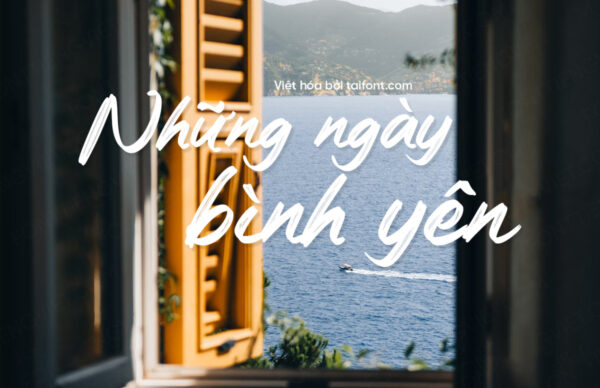
Giới thiệu về Font TF Realistic Theory Việt hóa
TF Realistic Theory Việt hóa là một font chữ Brush độc đáo, nổi bật với thiết kế tự do, phóng khoáng và đầy cá tính. Font này mang đến vẻ ngoài ngẫu hứng, năng động và rất riêng, gợi cảm giác về những nét cọ được phẩy một cách tự do, đầy năng lượng. Đây là lựa chọn lý tưởng để tạo điểm nhấn thị giác mạnh mẽ và gây chú ý ngay lập tức, đặc biệt trong các thiết kế liên quan đến du lịch, mỹ phẩm và các lĩnh vực đòi hỏi sự sáng tạo.
Với đặc điểm là nét brush to, đậm, dứt khoát và tính thẩm mỹ cao, Realistic Theory là lựa chọn hoàn hảo cho các thiết kế muốn truyền tải sự mạnh mẽ, hoài niệm và sự độc đáo, đặc biệt là trong các lĩnh vực:
- Thiết kế du lịch: Hoàn hảo để sử dụng cho logo các công ty du lịch, tiêu đề tạp chí du lịch, hoặc các ấn phẩm quảng bá tour. Nét chữ mạnh mẽ của font giúp truyền tải cảm giác phiêu lưu, khám phá và đầy năng lượng, thu hút những người yêu xê dịch.
- Thiết kế mỹ phẩm: Lý tưởng cho bao bì, nhãn mác, hoặc các ấn phẩm quảng cáo của các sản phẩm làm đẹp, mỹ phẩm. Font này giúp truyền tải vẻ đẹp tinh tế, sang trọng và độc quyền của sản phẩm, nâng tầm giá trị thương hiệu.
- Thiết kế bao bì sản phẩm: Phù hợp để sử dụng trên nhãn mác, bao bì của các sản phẩm có phong cách ngẫu hứng, năng động, đặc biệt là các sản phẩm liên quan đến giới trẻ. Font này giúp sản phẩm trở nên nổi bật và thu hút.
- Thiết kế poster và banner: Tuyệt vời để tạo các tiêu đề chính (headline), slogan, hoặc thông điệp quảng cáo trên poster, banner, hoặc bất kỳ ấn phẩm nào cần sự chú ý tối đa. Nét chữ tự nhiên của font giúp thông điệp của bạn nổi bật, dễ đọc và truyền tải một cách hiệu quả.
Với TF Realistic Theory Việt hóa, bạn có thể dễ dàng thổi hồn mạnh mẽ, sự độc đáo và cá tính vào các thiết kế, tạo ra những sản phẩm không chỉ đẹp mắt mà còn cực kỳ ấn tượng và có khả năng thu hút sự chú ý tối đa.
Font Việt hóa TF Realistic Theory